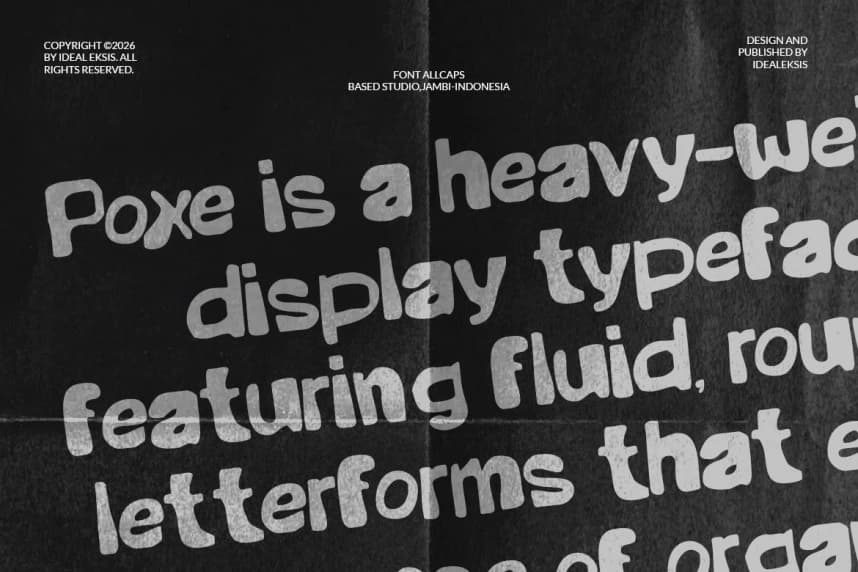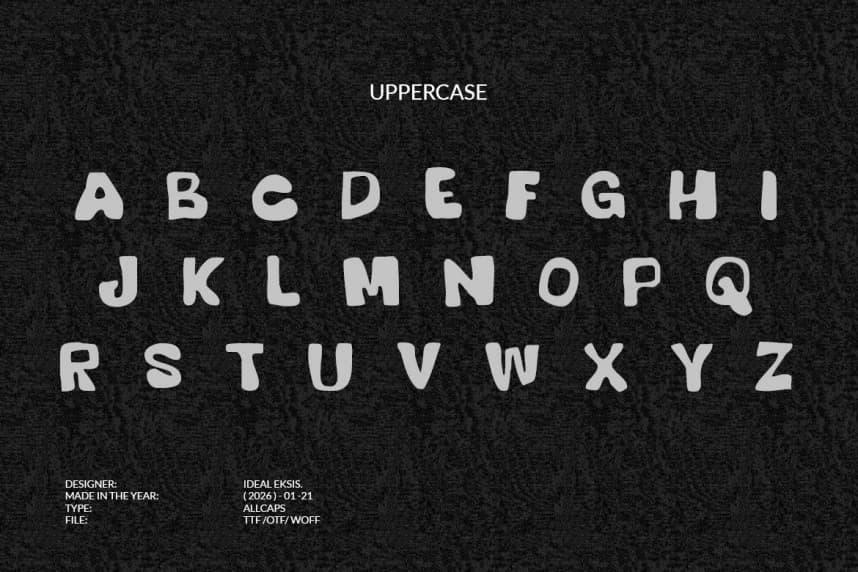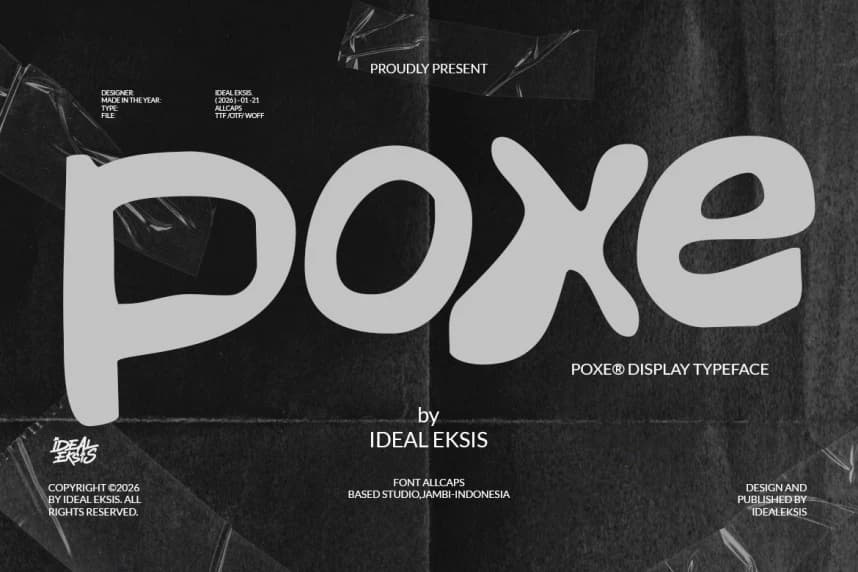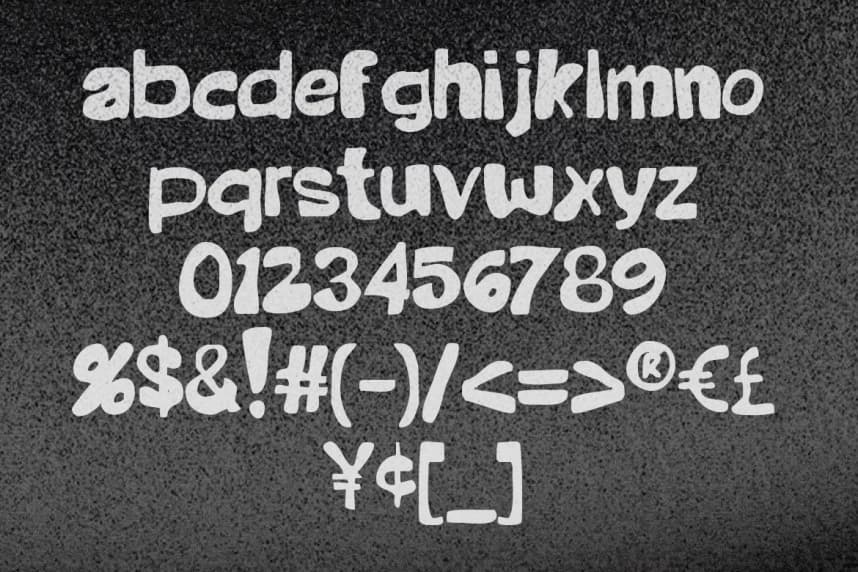
Poxe Font, organik bir hareket hissi uyandıran akıcı ve yuvarlak harf biçimlerine sahip, ağır bir gösterişli yazı tipidir. Çizgileri kalın ve tutarlı olup uçlar yumuşaktır; keskin kenarların oluşmasını engeller ve bu da dostane ama etkileyici bir estetik yaratır.
Poxe Font, organik bir hareket hissi uyandıran akışkan, yuvarlak harf biçimlerine sahip ağır ağırlıklı bir gösterişli yazı tipidir. Çizgileri kalın ve tutarlı olup uçları yumuşak olan, sert kenarları ortadan kaldırarak dostça ama çarpıcı bir estetik yaratır.